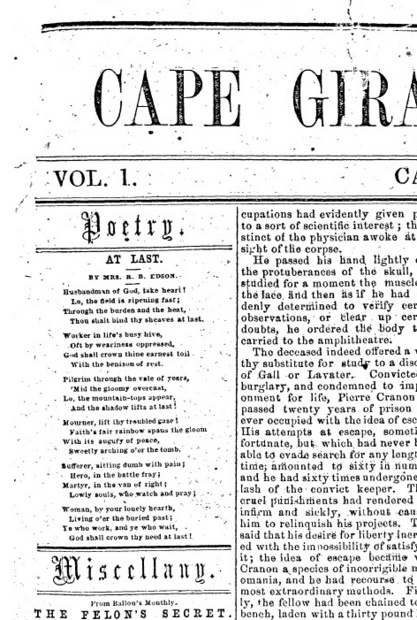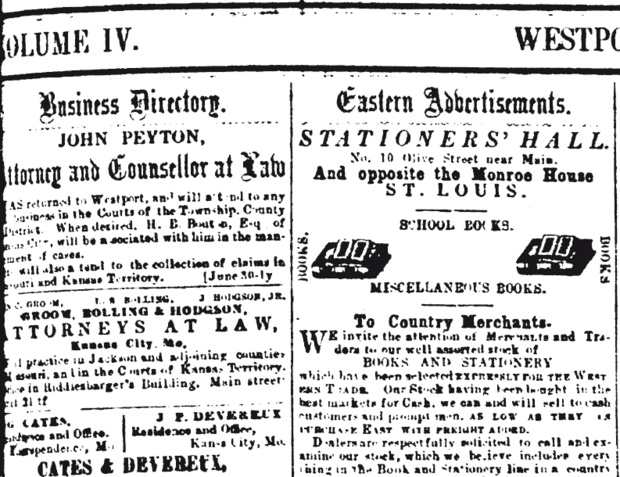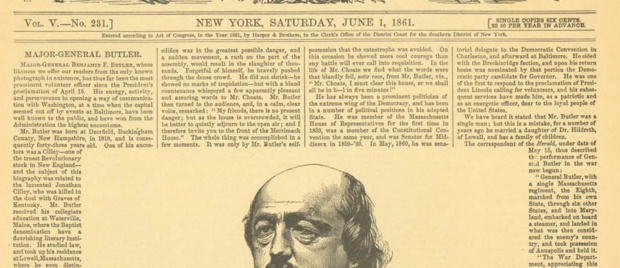
Zeitung der USA um 1860 nachempfinden: welche Schriften passen?
ich möchte eine Zeitschrift aus der Ära des US-Bürgerkriegs nachempfinden.
Welche TTFs könnte ich verwenden, um Artikel wie diese typografisch einigermaßen glaubhaft nachzuahmen?
Für die gebrochenen Elemente passt so etwas wie Wedding Text
Die typische Schrift dieser Zeit ist die schottische klassizistische Antiqua. Dazu gehört Nick Shinns Scotch Modern, die auf der Schrift eines Textes von 1873 beruht (allerdings keine genaue Digitalisierung ist). Ein anderer Vertreter dieser Gruppe ist die Modern Extended von URW (Digitalisierung einer Monotype-Schrift von 1902). Von Monotype selbst gibt es eine Digitalisierung, die vermutlich auf einem höheren Schriftgrad derselben Schrift beruht: die Monotype Modern. Die könntest Du für Überschriften verwenden; sie enthält auch einen schmalen Schnitt.
Für den in der Regel recht klein gesetzten Zeitungstext waren die sogenannten Ionic-Schriften typisch (ob eine solche in den oben abgebildeten Zeitungen verwendet worden ist, kann ich wegen der kleinen Bilder nicht sagen). Die Monotype Ionic stammt laut Linotype von 1821; ein anderes Beispiel ist Bitstreams News 701, von der ich jedoch nicht weiß, ob sie auf einer Vorlage aus der Zeit beruht.
Es gibt neben diesen sauber digitalisierten auch absichtlich unsauber digitalisierte Schriften, die nach Bleisatz aussehen sollen und zum Teil auch passen, beispielsweise die Schriften von Archive Type.